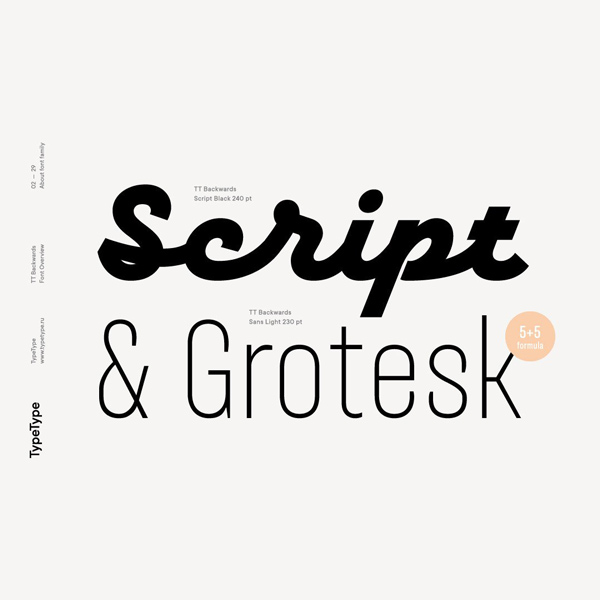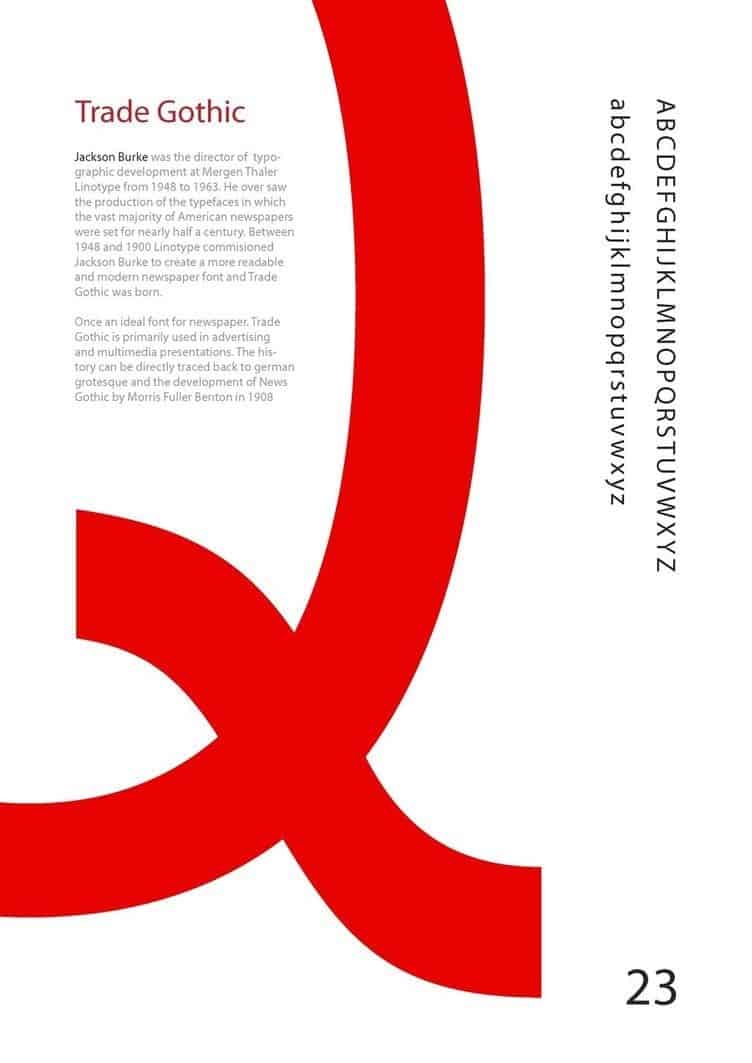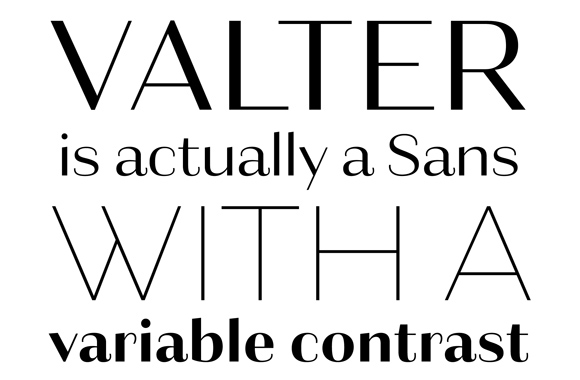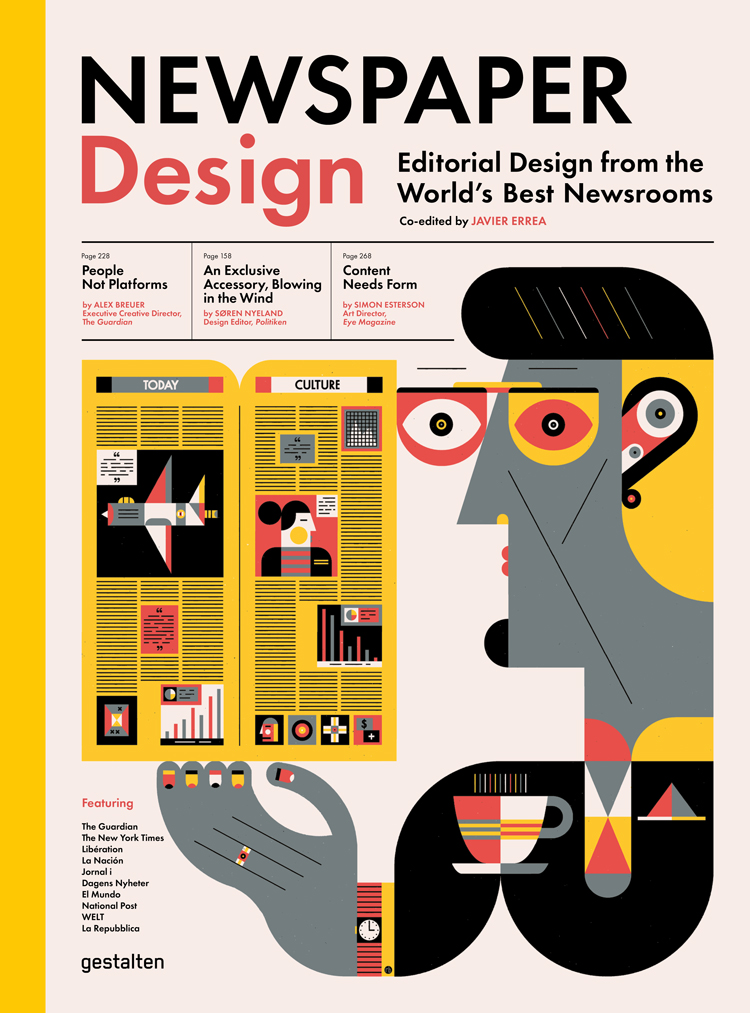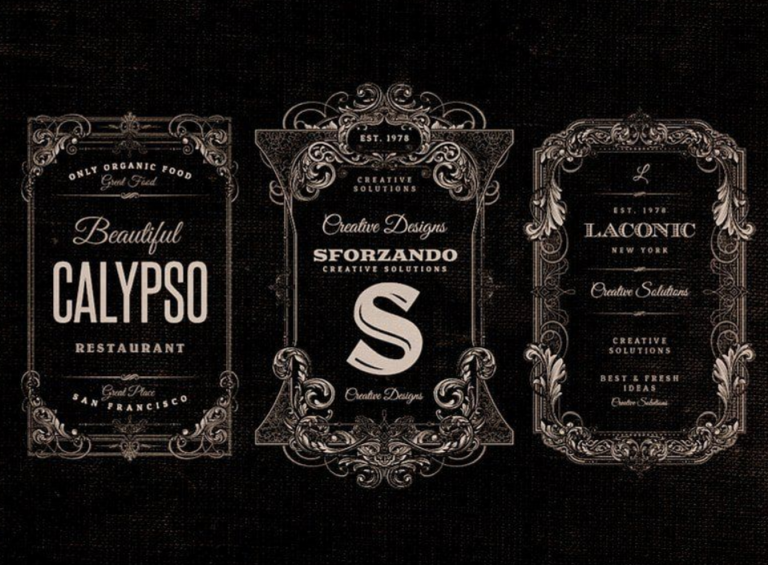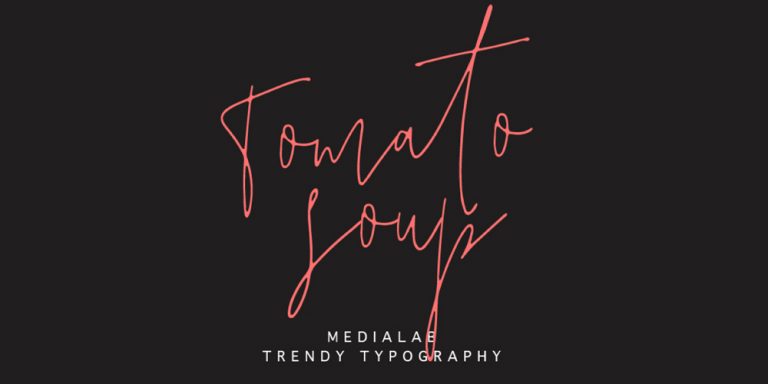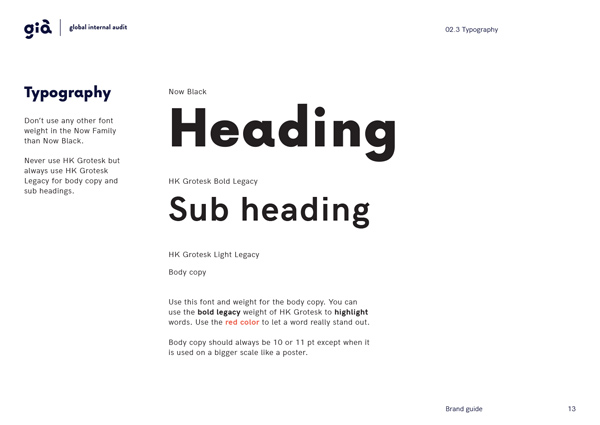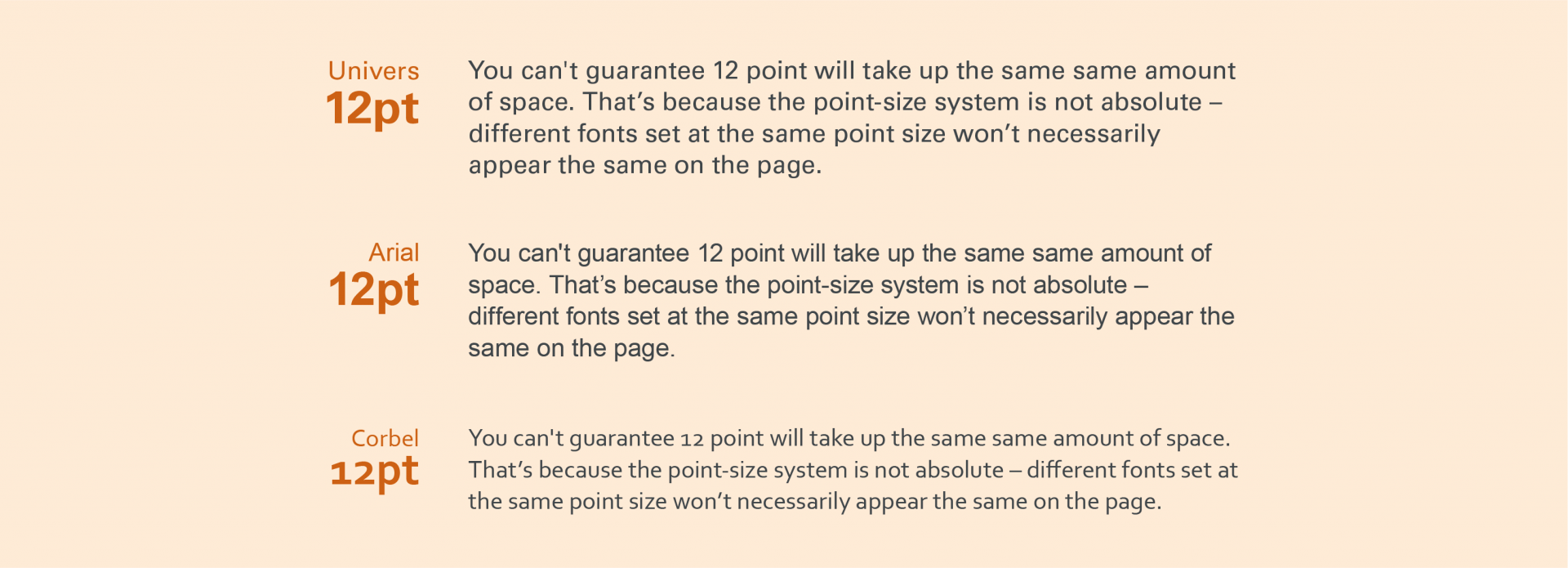
8 cách kết hợp font chữ hiệu quả nhất khi thiết kế cho doanh nghiệp năm 2024
Kết hợp font chữ là cả một nghệ thuật. Bởi lẽ kết hợp font chữ sao cho đẹp và ấn tượng là không hề đơn giản. Font chữ là một thành phần quan trọng trong thương hiệu, có tác động rất lớn đến "cảm xúc"  của khách hàng. Hãy cùng Bee Art tìm hiểu về 8 cách kết hợp font chữ hiệu quả nhất khi thiết kế cho doanh nghiệp năm 2024.
8 cách kết hợp font chữ hiệu quả nhất khi thiết kế cho doanh nghiệp năm 2024
Trong thế giới ngày nay, nơi mà thông tin được truyền đạt qua nhiều phương tiện truyền thông khác nhau, việc chọn lựa và kết hợp font chữ phù hợp đã trở thành một yếu tố quan trọng không thể bỏ qua trong thiết kế đồ hoạ. Font chữ không chỉ đơn thuần là các ký tự để truyền tải văn bản, mà còn là một công cụ mạnh mẽ để truyền đạt cảm xúc, tạo ra ấn tượng và thiết lập sự nhận biết thương hiệu.
Font chữ có khả năng truyền đạt thông điệp. Mỗi font chữ mang đậm một cái phong cách riêng, từ sự truyền thống, chính thống đến sự hiện đại, cá nhân. Lựa chọn và kết hợp font chữ phù hợp không chỉ giúp văn bản trở nên dễ đọc mà còn giúp truyền tải một thông điệp cụ thể. Ví dụ, sử dụng font chữ chuyên nghiệp và trang trọng có thể phù hợp với một bản báo cáo kinh doanh, trong khi một font chữ vui nhộn và phóng khoáng sẽ là lựa chọn thích hợp cho một thẻ mời tiệc.
Ngoài ra, font chữ cũng đóng vai trò quan trọng trong việc xây dựng và củng cố nhận biết thương hiệu. Khi một font chữ được sử dụng liên tục trong các tài liệu, quảng cáo và trên các sản phẩm của một thương hiệu, nó tạo ra một hình ảnh nhận biết dễ nhận ra cho thương hiệu đó. Ví dụ, font chữ của Coca-Cola hay Nike đã trở thành biểu tượng của thương hiệu và không cần thêm bất kỳ logo nào khác để người tiêu dùng nhận biết.
Đồng thời, font chữ cũng góp phần vào việc tạo ra không gian và cảm xúc cho thiết kế đồ hoạ. Sự lựa chọn và kết hợp font chữ có thể làm nổi bật một cảm xúc nhất định, từ sự vui vẻ, thoải mái đến sự nghiêm túc, trang trọng. Ví dụ, một font chữ vui nhộn và phóng khoáng có thể làm cho độc giả cảm thấy vui vẻ và thân thiện, trong khi một font chữ nghiêm túc và cổ điển có thể tạo ra một cảm giác nghiêm trang và uy nghiêm.
Designer thường xuyên phải làm việc với rất nhiều font chữ khác nhau nhằm tạo ra một tổng thể thu hút và xây dựng phân cấp thị giác một cách hiệu quả. Trong trường hợp không có những luật lệ nghiêm ngặt hay các quy tắc khoa học để có thể áp dụng, bạn cần phải liên tục thử nghiệm và kiểm tra lại các kĩ thuật để có thể tạo ra được một cấu trúc typography ổn định. Bằng cách quan sát và học tập những phương pháp tốt nhất của quá trình thiết kế con chữ, bạn sẽ có khả năng chỉ ra được liệu những kiểu chữ nào khi kết hợp với nhau sẽ cho ra kết quả phù hợp nhất.
Cách kết hợp font chữ hiệu quả nhất khi thiết kế
Điều tuyệt vời nhất về nghệ thuật và thiết kế là mỗi khi bạn tạo ra một hình dạng, kiểu dáng mới, bạn có thể thỏa sức khám phá các phong cách, kĩ thuật và những sự phối hợp khác nhau để truyền tải đi một thông điệp. Như một người đã từng nói rằng: Phải hiểu được những điều cơ bản nhất của nghệ thuật thiết kế, bạn mới có đủ khả năng để bước qua ranh giới của các luật lệ.
1. Kết hợp font chữ bổ túc
Hầu hết các kiểu chữ đều có khả năng khơi gợi nên một phản hồi mang tính cảm xúc từ phía người dùng. Những kiểu chữ có xu hướng biểu đạt những trạng thái cảm xúc cũng như tính chất khác nhau, chúng cũng nên được kết hợp dựa trên sự phù hợp của những đặc tính đó. Tuy nhiên, trong một số trường hợp nhất định, những kiểu chữ ở hai thái cực đối lập lại có thể song hành cùng nhau một cách tương đối hiệu quả. Điểm khác biệt làm nên mỗi kiểu chữ thường mang lại sự cân bằng cho những kiểu chữ đối lập chúng và tạo nên một thiết kế hài hòa, tinh tế.
ket hop font chu 2.jpg
Kết hợp font chữ bổ túc
Ví dụ, nếu bạn đang thực hiện thiết kế với một font mang tính chất mạnh mẽ, đồ sộ (giống như font ở hình phía trên) thì hãy kết hợp nó với một font nhỏ gọn, thanh lịch. Điều này sẽ cho bạn khả năng tạo ra một thiết kế cân bằng, dễ chịu. Khi đưa ra quyết định kết hợp đó, bạn sẽ thường thấy rằng bản thân phụ thuộc nhiều vào cảm xúc cá nhân và điều này thì không sao cả. Hãy bình tĩnh. Việc tìm kiếm và kết hợp đúng font với nhau không hề đơn giản và đòi hỏi bạn phải luyện tập thường xuyên để có thể đạt đến cảnh giới đó.
2. Kết hợp font chữ có chân và font chữ không chân
Đây là một kết hợp thuộc hàng kinh điển, được sử dụng tương đối hiệu quả trên cả các dự án website cũng như các dự án in ấn. Nếu bạn không có nhiều thời gian trong việc lựa chọn, hãy kết hợp giữa một font serif (font chữ có chân) và một font sans serif (font chữ không chân). Điều này sẽ luôn đảm bảo tính rõ ràng cho nội dung văn bản của bạn. Ví dụ, nếu bạn nhìn vào bài báo phía dưới, bạn có thể thấy ngay rằng Trade Gothic là một kiểu chữ năng động và thanh lịch trong khi Bell Gothic. Ngược lại, có một sự hiện diện áp đảo. Việc kết hợp hai kiểu chữ này lại có lẽ sẽ không phải là lựa chọn tối ưu nhất để nhận dạng nội dung văn bản.
Kết hợp font chữ có chân và font chữ không chân
3. Tạo kết cấu tương phản khi kết hợp font chữ
Một trong những lý do giải thích cho sự hiệu quả của việc kết hợp giữa font chữ có chân và font chữ không chân là bởi vì chúng có khả năng tạo ra một sự tương phản thị giác khi đứng cạnh nhau. Sự tương phản có thể đạt được theo nhiều phương pháp – sử dụng màu sắc, các phong cách, độ dày/mỏng của yếu tố, kích thước và khoảng cách.